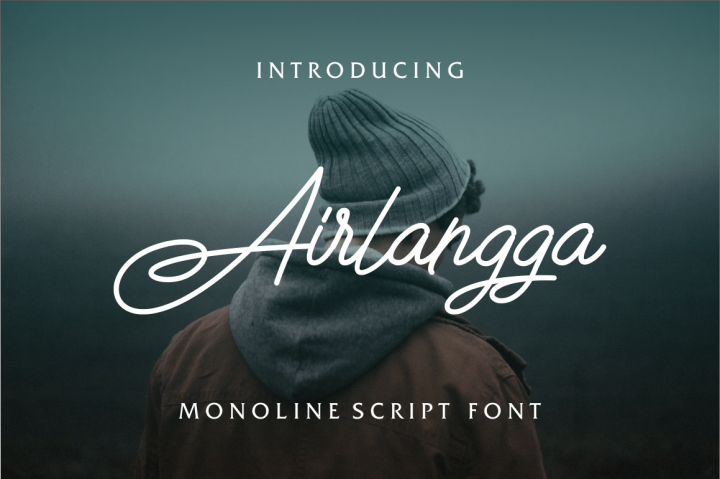
Airlangga Script Font – Fonte Grátis
Airlangga Script Font
A Airlangga Script Font é uma opção perfeita para quem procura um tipo à mão livre moderno e elegante que se move naturalmente ao longo do baseline. Introduzida pelo designer zziplex, a Airlangga tem um estilo casual e autêntico, combinando perfeitamente com os projetos de branding, logos, capas de blogs, convites para casamentos, t-shirts, e até mesmo cartazes. Com muitos recursos e facilidade na sua utilização, esta fonte é ideal tanto para novatos como para designers mais experientes que buscam expressar uma identidade visual única em suas criações. Seja você um aspirante a designer ou um profissional em busca de estímulos criativos, o Airlangga pode ser um aliado valioso no seu processo de trabalho. Englobando diversos usos práticos e criativos, esta fonte é uma escolha certa para quem procura expressar sua personalidade através do design.